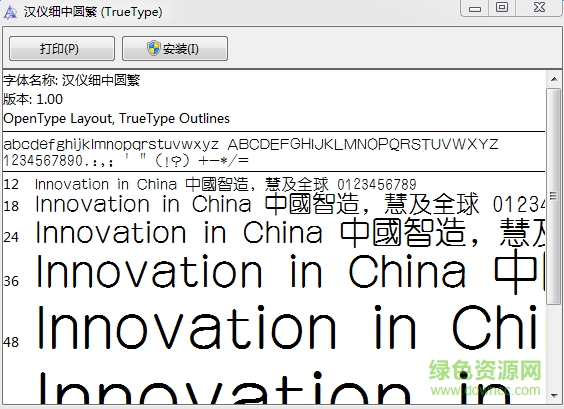
軟件介紹 軟件標(biāo)簽: 漢儀字體 字體 漢儀細中圓繁是漢儀字體中的一款繁體字體,這款字體最大的特點就是比較細,所以寫出來的字也是很細的,但是卻很好看,可以用于很多環(huán)境,大家如果有需要的話就來綠色資源網(wǎng)下載吧。安裝說明:1.在綠色資源網(wǎng)下載字體包,并解壓縮2.最簡單的安裝方法:雙擊字體文件,點擊安裝按鈕即可2.批量安裝方法:將字體文件放到C:\Windows\Fonts溫馨提示:本站所有字體資源僅供個人學(xué)習(xí)與參考,如需商業(yè)使用請到相關(guān)官網(wǎng)授權(quán) 本字體如果商用,請聯(lián)系漢儀字體官方獲得授權(quán)。 軟件截圖 上一張下一張(1 / 1) 安裝詳細截圖 其他版本下載 標(biāo)題 大小 更新日期 下載 下載地址 電腦版 漢儀細中圓繁 點擊報錯 軟件無法下載或下載后無法使用,請點擊報錯,謝謝! 關(guān)閉報錯反饋 請描述您所遇到的錯誤,我們將盡快予以修正,謝謝! *必填項,請輸入內(nèi)容 本類最新 漢儀孟瑞體ttf v1.0 官方版 漢儀字庫免費 132款 阿里巴巴普惠字體 官方ttf版 漢儀字體打包大全 for Mac 蘋果電腦版_ 共131款字體 漢儀純愛情書拼音體 ttf版 漢儀北魏寫經(jīng)w字體 免費版 相關(guān)文章 Photoshop字體安裝使用方法和技巧 如何解決“無法新增字體”問題 Win 7系統(tǒng)安裝字體方法 網(wǎng)頁字體大小設(shè)置方法 怎么改網(wǎng)頁字體大小 在Linux系統(tǒng)中安裝字體的幾種方法 windows7字體顯示問題:打開某些程序的時候顯示的是亂碼 用戶評論 熱門評論 最新評論 發(fā)表評論 查看所有評論(0) 昵稱: 請不要評論無意義或臟話,我們所有評論會有人工審核. 字?jǐn)?shù): 0/500 (您的評論需要經(jīng)過審核才能顯示)